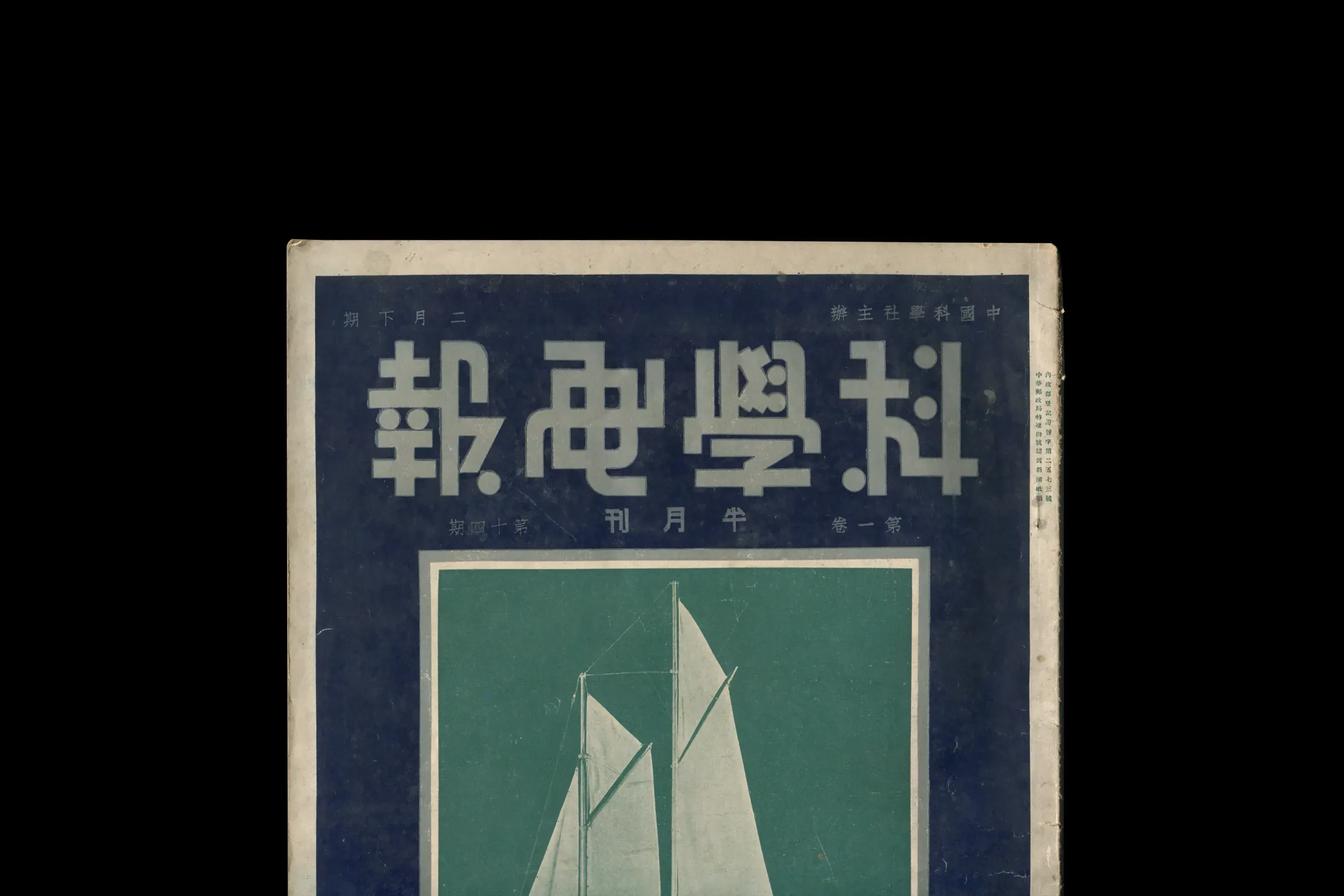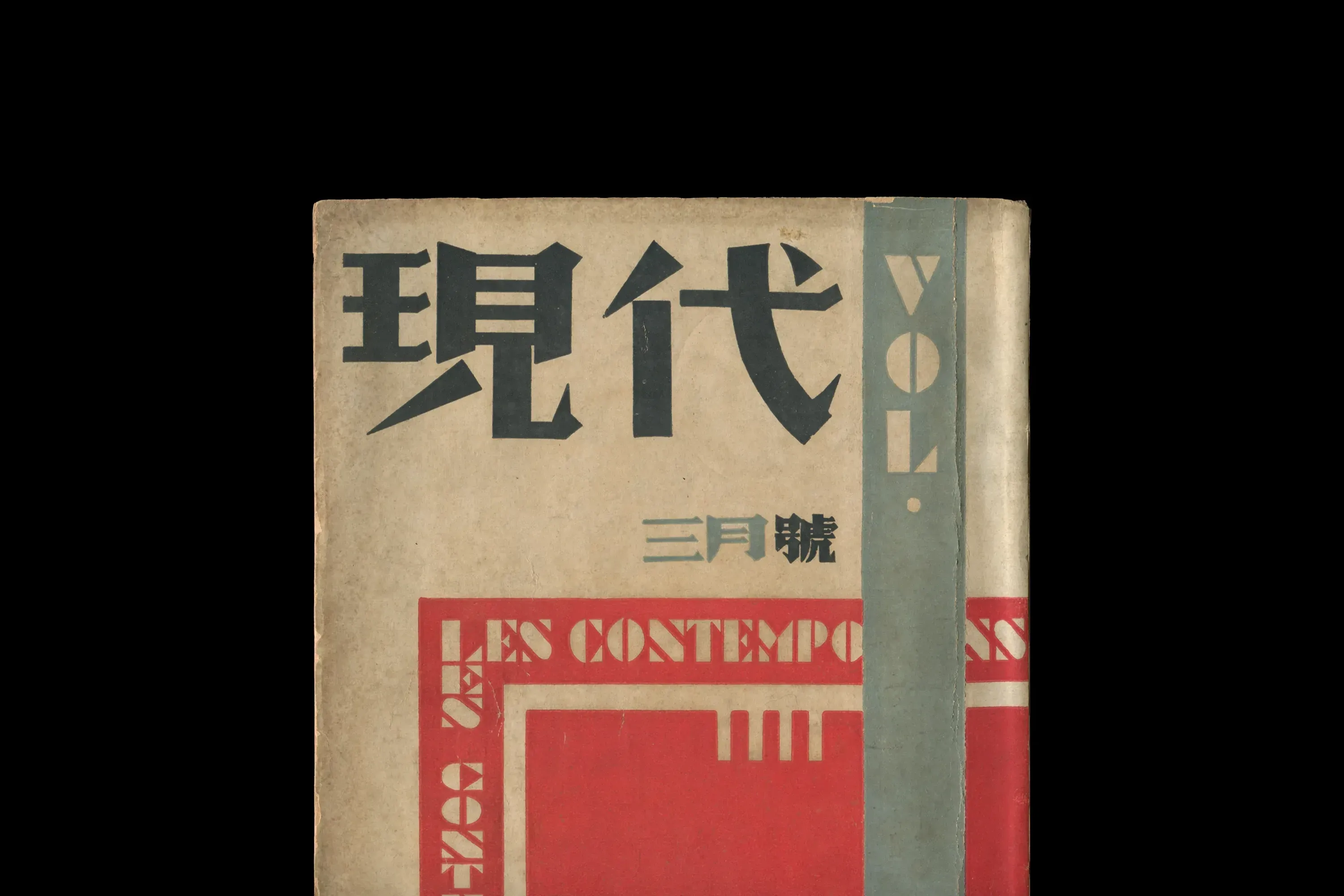
作为 Art Deco 装饰艺术的重要原乡,上海孕育了独特的都市文化与摩登气象。为延续这份源流与文脉,"上海摩登体"由此诞生,企望重拾文字与城市精神、文化认同间的关联,成为个体与城市记忆的纽带,也成为连接世界、通向未来的文化传承。Right quote
上海摩登体 一座城及其所连接的城市,是一个什么样的地方?最具启发性的论述,或许是卡尔维诺在《看不见的城市》的前言中所写道的:"这些城市是众多事物的一个整体:记忆的整体,欲望的整体,一种言语的符号的整体;正如所有的经济史书籍所解释的,城市是一些交换的地点,但这些交换并不仅仅是货物的交换,它们还是话语的交换,欲望的交换,记录的交换。"
字体,是一种"言语的符号",而当追溯中文字体设计的发展史时,我们发现:它的诞生与发展,正是上述"交换"的结果——而那个"交换的地点"——那座城市,便是上海。
二十世纪二十年代末,伴随着西方建筑、工业、商品、娱乐与媒体思潮的涌入,工商业在上海迅速发展,上海成为了有着"东方巴黎"之称的国际贸易商都;而中文字体设计的繁盛景象,正是依托在这密集"交换"的商业世界上生成。字体,并非孤立地存在,作为一种"视觉传达"手段,它出现在建筑的霓虹招牌,商品的包装标识,流动的广告招贴上……西方商品("洋货")及其视觉行销手段的涌入,启发了中国人开始模仿与发展这些商业美术语言,而应循着其后上海本土工商业的崛起及"国货运动",跃然其上的中文字体开始成为"国货"商品的重要的视觉标识,纷繁而多样的中文美术字开始被创造出来。
在这些契机之下,二十世纪二十至四十年代的上海,成就了中文字体设计史上最为辉煌的篇章,这一时期所留下的文字视觉资产,不仅仅出现在书籍、报纸、期刊等出版媒介上,更伴随着万花筒般的商品世界的流转,在银行大楼、百货公司、大饭店、咖啡厅、影剧院、跑马场、歌舞厅等都会场景中,沁入了人们的生活…… 1930-40年代上海纺织印染厂商标。 1930年代上海中国国货公司,包装。 "最新外衣"招贴设计,张以恬设计,
选自《现代中国商业美术选集》第一集。左旭初藏。 《黑白美术图案字》,蔡忱毅编,上海新亚书店,1946年。20世纪初期是中国美术字活跃的时期。伴随着以上海为中心的商业发展,知识分子的海外交流,中国的文艺界也开始受到日本和西方的强烈影响,最前卫,最具实验性的图案字在包装、广告、招牌上巍然成风,其中不乏很多类似印刷黑体的美术字……干练而富有几何感的黑体美术字,既有新鲜感,识别度又高,风头盖过了以往商号常用的粗楷体,也让用于正文印刷的黑体大为盛行,常用于书籍和报刊印刷的标题中。(该图文选自《从字体开始——设计改变的生活与社会》,The Type 编著,广西师范大学出版社,2023年)。
在数码文字将人们之于字体的视觉经验趋于同一而逐渐失联的今天,"上海摩登体"字体的研发与诞生,正试图重建:人们对于字体——这一实则弥散在人们的生活日常中的——视觉文化的体认。作为一款具有强烈视觉特征的"标题字","上海摩登体"的字形,展现了字体同图案、纹饰一样作为一种"装饰形象"的象征力量。这一象征所连接的是一个世纪之前在上海成为"繁华都会"之际涌动在这座城市中的精神——正如"摩登(Modeng)"所隐喻的:尽管"摩登"脱胎于"modern"的音译,诞生在上海;但上海所演绎的"摩登"景象却绝非是对西方"现代派"艺术的一味摹写,而是在中国文化与社会自身的土壤与底色之上,脱化出了自己的语言与视界。
1931年《学生杂志》杂志封面,
设计:钱君匋,商务印书馆。
1935年《建筑月刊》杂志封面, 上海市建筑协会。
1934年《电声》杂志封面,三和出版社。
1934年《科学画报》杂志封面, 中国科学社。
1933年《现代》杂志封面,现代书局。
左起顺时针:
- 《现代学生》封面文字,陈之佛设计。陈之佛充分发挥了他在日本求学期间打下的坚实的图案功底,同时举重若轻地将欧洲风行的装饰派、立体主义艺术等融汇运用,创造出了紧扣时代又别具一格的装饰风格。(以上图文选自《从字体开始——设计改变的生活与社会》,The Type 编著)。《上海字记》中介绍:"陈之佛是中国第一位赴日本学习工艺图案的留学生,其于1924年归国后曾在上海创办尚美图案馆,为印染业培养设计人员"。
- 1935年《进行曲选》书籍封面,设计:钱君匋,开明书店。
- 1940年代《武则天》话剧节目单,上海剧艺社。
- 1927年徐志摩散文集《巴黎的鳞爪》,封面装帧设计:闻一多。(图文来自:《从字体开始——设计改变的生活与社会》,The Type 编著)
- 1928年《奔流》第1卷第5期,杂志封面,主编:鲁迅,北新书局。铅印。(图文来自:《从字体开始——设计改变的生活与社会》,The Type 编著)
- 1930年《伟大的恋爱》书籍封面,设计:钱君匋(图文来自:《从字体开始——设计改变的生活与社会》,The Type 编著)
- 1933年《时代妇女》书籍封面,设计:钱君匋,光华书局。(图文来自:《从字体开始——设计改变的生活与社会》,The Type 编著)
- 《现代学生》封面,陈之佛设计。
这种脱化,使得艺术具有了一种打破"象牙塔"的普世的力量。正如施蛰存在1933年的《现代》杂志中曾写下被认为是"中国现代派诗歌"宣言般的文字:"……纯然的现代的诗。它们是现代人在现代生活中所感受的现代的情绪,用现代的辞藻排列成的现代的诗形。……所谓现代生活,这里面包含着各式各样独特的形态:汇集着大船舶的港湾,轰响着噪音的工场,深入地下的矿坑,奏着Jazz乐的舞场,摩天楼的百货店,飞机的空中战,广大的竞马场……甚至连自然景物也与前代的不同了。这种生活所给与我们的诗人的感情,难道会与上代诗人们从他们的生活中所得到的感情相同的吗?" 再如中国图案学体系的奠基人雷圭元先生留法亲历西方的艺术浪潮后在1934年撰文的《近今法兰西图案运动》中所写:"动的、高速度的、几何形的、机械的轮廓,整齐而有规律地活动,电气炫目的闪亮,无线电的刺耳的声浪,不知不觉间,这些线和形,汇集在图案家的脑子里了。那商业和工业的竞争,而使图案家的心手跟着也起来呼应着动的、机械的构成,产生了无数的新的线条,新的色彩" ……
一个世纪之前,上海的"摩登文化"与"摩登艺术",是这些创作者们以自己的心与手,与时代、与社会相应的结果。这种相应,使得他们的书写、他们的图绘、他们的创造……连接起身处在一片土地上的每一个人。艺术,在此达成了一种连接。"上海摩登体",正企望重拾这种连接,愿这些字符如分子一般弥散在上海、中国与世界,弥散在现实与虚拟的不同位面与角落——将人们连接在一起。
SHANGHAI MODENG
上海摩登体(Shanghai Modeng)是中国首个以城市文化为源流的中西文字体。字库按照GB2312国标标准研发。这款字体溯源了1930至40年代伴随着上海都市文化的起源与涌现,影响与遍及了各种视觉文化形态的装饰艺术(Art Déco)运动。这款字体的设计不是对装饰艺术风格的形式复刻,而是在秉承装饰艺术运动融合多元文化与创新未来的时代精神的同时,通过独特的字形语言,向城市文明演进的过去、现在与未来的提问。
上海摩登体以现代字库技术为基底,突破传统汉字结构,将装饰艺术风格的几何美学精髓注入汉字骨骼。其笔形系统尝试革新——直线与圆弧的精密组合取代传统书写的自然笔触,笔画粗细均衡、刚柔相济,字体架构采用字面高耸的设计,犹如建筑般挺拔有力,在静态的几何秩序中迸发出向上的动感,使得每个字的结构充满了先锋性和想象力。
上海摩登体的西文字体既严格遵循与中文字体统一的设计逻辑,同时深入考量西文排版的语境特征,巧妙地在西文字体的传统与创新之间实现平衡。小写字母采用了较高的x高度,特意强调了字母的圆弧造型,与其他字身较窄的字母形成鲜明的对比,塑造出富有几何韵律的视觉张力。另外,西文字体通过OpenType字体技术,增加了西文字符的连笔功能,使得字符之间的组合灵活多变、自然流畅。
上海摩登体的阿拉伯数字采用富有弹性和力度的圆弧形线条,字形精致饱满,趣味生动。标点符号的设计延续了中文字形修长的视觉特征,重心上移,冒号、分号打破常规布局,从细微之处增强了上海摩登体的独特气质。
作为一款融合当代城市文化精神的创新字体,上海摩登体在历史传承与未来创新之间建立了对话。其富有表现力的现代几何造型,不仅能为品牌、广告、包装、游戏和出版物提供鲜明的视觉形象,还能在城市形象、空间叙事和文旅体验中展现其独特的风格与魅力。 上海摩登体由汉唐文化发起研发并出品,向社会开源共享,可登录"上海摩登体"字体官方网站下载并应用该字体。